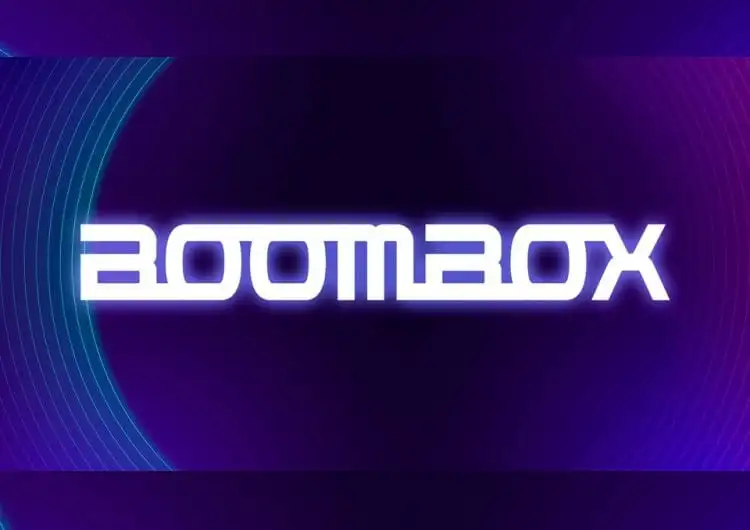
A fonte “Boombox Display Font” criada por Jonathan Paterson é uma escolha perfeita para aqueles que buscam uma tipografia moderna e futurista. Desenvolvida com um estilo retro, ela transmite um leve toque de aventura espacial. Ideal para textos curtos que desempenham o papel de comunicações na borda de uma estação espacial durante uma viagem profunda pela galáxia. Com seu formato bold e futurista, a “Boombox Display Font” torna-se um recurso ideal tanto para designers como para empresas criando logotipos ou projetos publicitários. Suas linhas retas e os espaçamentos claros remetem ao mundo da mídia digital, mas ainda assim mantêm uma atmosfera nostálgica do passado, fazendo-a perfeitamente adaptável a qualquer ambiente visual desejado. Esta fonte é certamente um trunfo para aqueles que buscam um estilo único e vibrante, que se adapta perfeitamente ao universo digital contemporâneo. Além disso, seu design é tão versátil quanto a sua natureza: pode ser usada em tudo do logo de uma empresa até o texto nas bordas de uma tela de vídeo espacial.